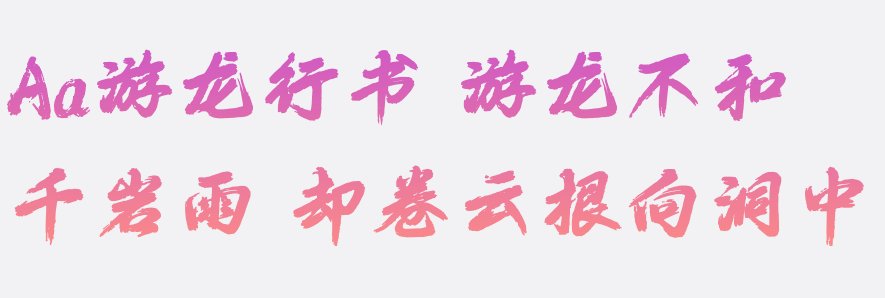
行书字体一向以其鲜明的轻重顿挫而著称,然而《Aa游龙行书》却在众多字体中独树一帜。它的特点不在于明显的起承转合,而是在于那如游龙般流畅的线条,以及末笔拖长的潇洒飞白,给人一种十足的动感。
首先,字体的线条流畅而自由。笔画间无明显的分隔,仿佛是一条游龙在纸上畅游,从一个字到下一个字,自然而无拘束。这种流畅性令人联想到自由奔放的艺术表现,充满了活力和生气。
其次,末笔拖长的潇洒飞白是其特色之一。这种特殊的笔画表现出一种豁达的情感,仿佛书写者正在释放内心的情感,不受拘束地书写。这种飞白的运用使字体更加生动,令人感受到一种自由的情感。
《Aa游龙行书》的应用场景广泛。它常常出现在书法作品、书法展览和艺术品中。其独特的特点使得它在传达情感和表达自由创意时大放异彩。无论是书法家还是艺术家,都能够通过这一字体表达出他们的独特风采和情感。